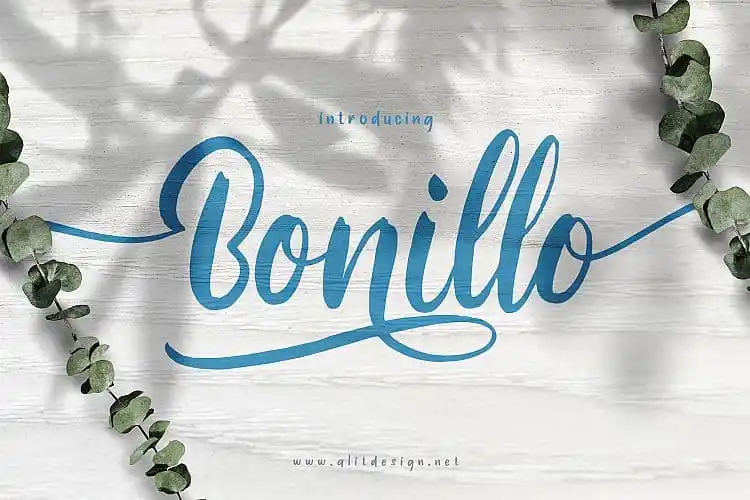
Bonillo Script Font – Fonte Grátis
Bonillo Script Font
A Bonillo Script Font é uma nova escolha para quem busca beleza moderna em suas escritas manuscritas. Desenvolvida por alit suarnegara, essa fonte brush script foi criada com a sensação de um pincel natural, fornecendo um estilo elegante que se encaixa perfeitamente nos conceitos de design do momento, que valorizam cores naturais como o amarelado escuro e a terra seca escura. O destaque é o seu conjunto de alternativas de caracteres, que oferecem uma vasta gama de opções para decorar ou tornar sua escrita mais bela. Se você busca adicionar um toque autêntico à sua coleção de fontes da loja, a Bonillo Script Font é sem dúvida um excelente candidato.